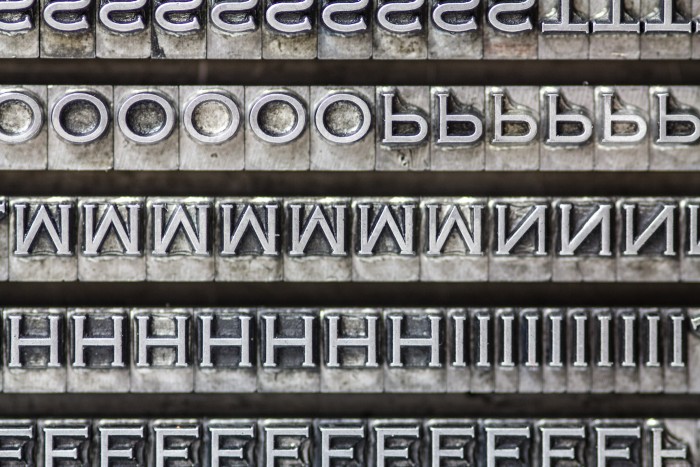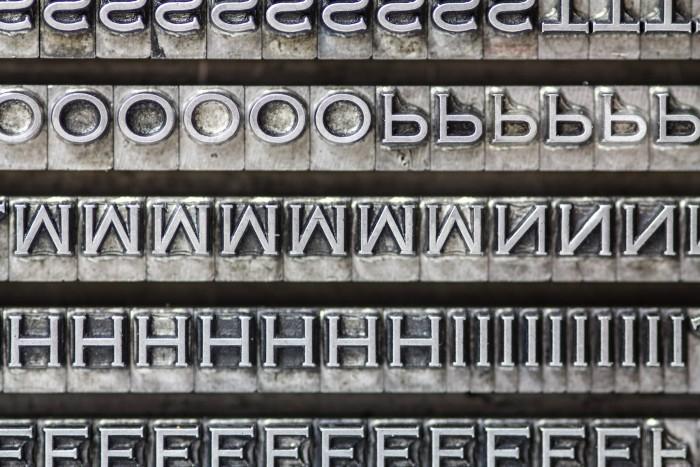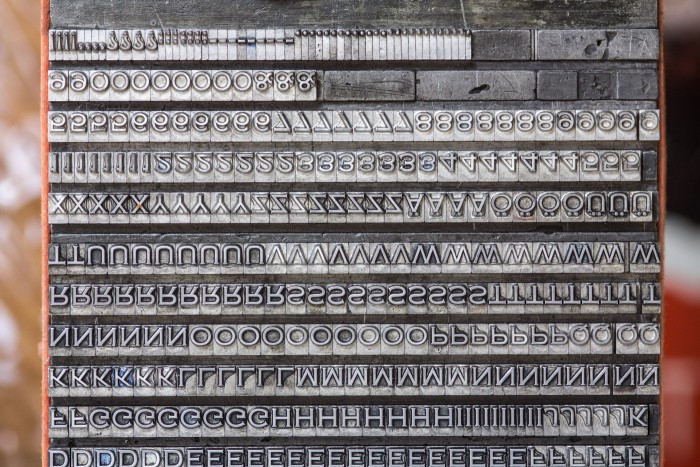
Bleisatzschrift „SPARTAN“, aber kein Futura-Klon?
Moin, beim Aufräumen von Vaters Krempel waren auch einige SPARTAN-Setzkästen dabei. Eine Internetsuche führte mich aber nur zum Futura-Klon. Gab es zwei Schriften gleichen Namens?
Auch wenn das jetzt keine Antwort auf deine Frage ist: Wäre es vielleicht möglich, solch ein Foto dieser Schrift in möglichst hoher Auflösung zu erhalten?
Denn so ein Foto mit allen Figuren wäre der ideale Grundstock für eine 1A-Digitalisierung, da man hier neben den eigentlichen Glyphen-Konturen eben auch die genaue Position auf dem Kegel mit den Vor- und Nachbreiten sieht, und so eben nicht an der Zurichting fummeln muss.
Das wär echt super..
Die sieht jedenfalls hübsch aus! Die Buchstaben sind erstaunlich breit für eine Bleisatzschrift, finde ich. Durch die Form ihrer Serifen erinnert sie an die Copperplate …
Das Q ist schön!  :biglove:
Um zur Frage zurückzukommen: Das gibt es häufiger, dass Bleisatzschriften als Computerfonts anders heißen (manchmal sogar verschiedene Digitalisierungen derselben Schrift unter mehreren Namen) oder dass Computerfonts unter dem Namen einer Bleisatzschrift ganz andere Schriften sind ...
Gehört wahrscheinlich mit zur "Schöpfungshöhe" ... :schonklar:
Moin, beim Aufräumen von Vaters Krempel waren auch einige SPARTAN-Setzkästen dabei. Eine Internetsuche führte mich aber nur zum Futura-Klon.
Wo hast du denn gesucht? Typografie.info führt doch zur gewünschten Schrift bei Stephenson, Blake & Co:
Danke, der Zusatz „Stephenson Blake & Co“ führte zum Sucherfolg.
Ich suchte nach „Spartan Bleisatz“, „Spartan Font“ und „Spartan lead type“
Wo hast du denn gesucht? Typografie.info führt doch zur gewünschten Schrift bei Stephenson, Blake & Co:
Ich habe die Spartan als gußfrische neue Schrift von 3 Punkt bis 12 Punkt von der Gießerei Wagner in Ingolstadt in den 1990er Jahren gekauft. Es müßte also auch in Deutschland Matrizen dafür gegeben haben, nicht?
Wagner Ingolstadt hatte aber auch allerhand Restbestände an Matrizen aus vielen Gießereien Europas zusammengekauft ... sie waren ja quasi die Vorletzten, die noch Komplettguß gewerblich-industriell gemacht haben.